Современный шрифт и типографика (Илья Рудерман и Валерий Голыженков)
Оптические эффекты
Баланс форм и объемов
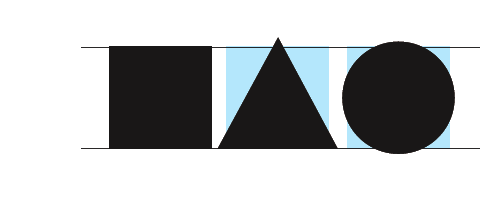
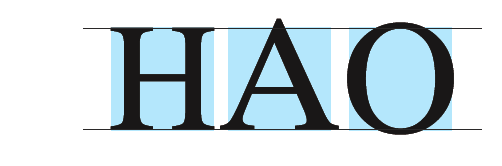
Баланс отношений прямоугольной и округлой формы
Баланс устойчивого и динамичного штриха
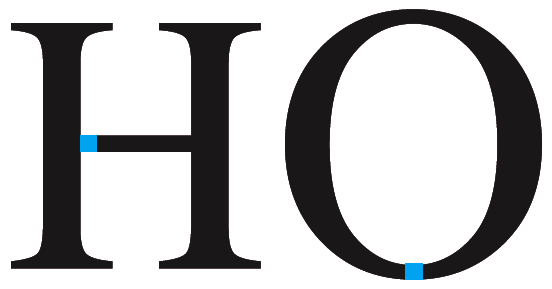
Горизонталь и вертикаль
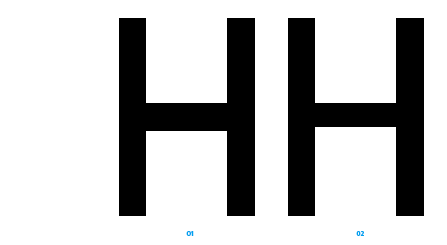
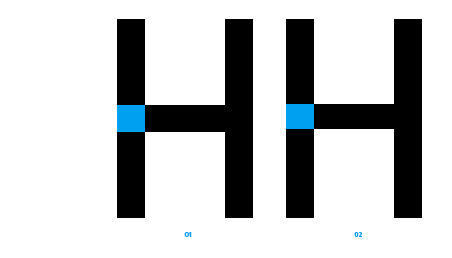
Баланс в круге
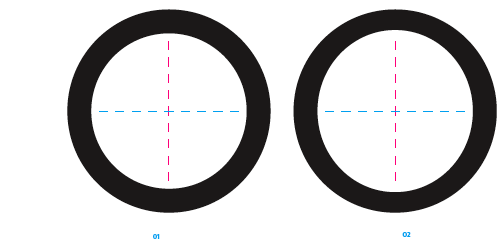
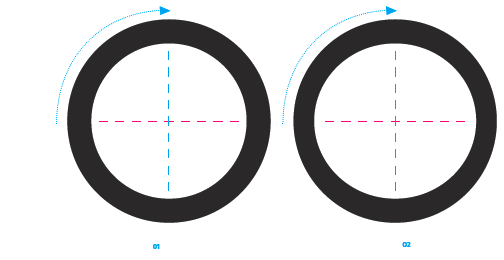
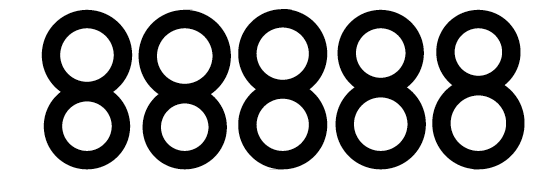
Диагональ
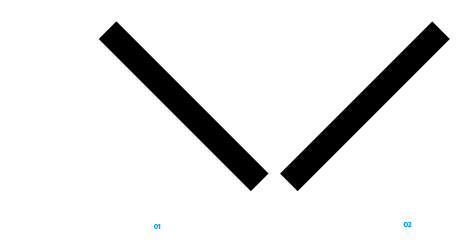
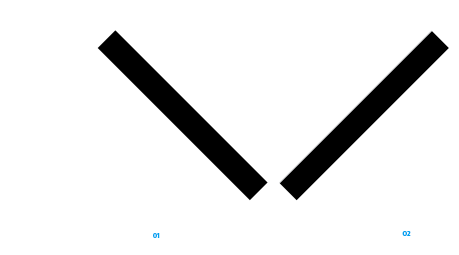
Эффект плавного скругления